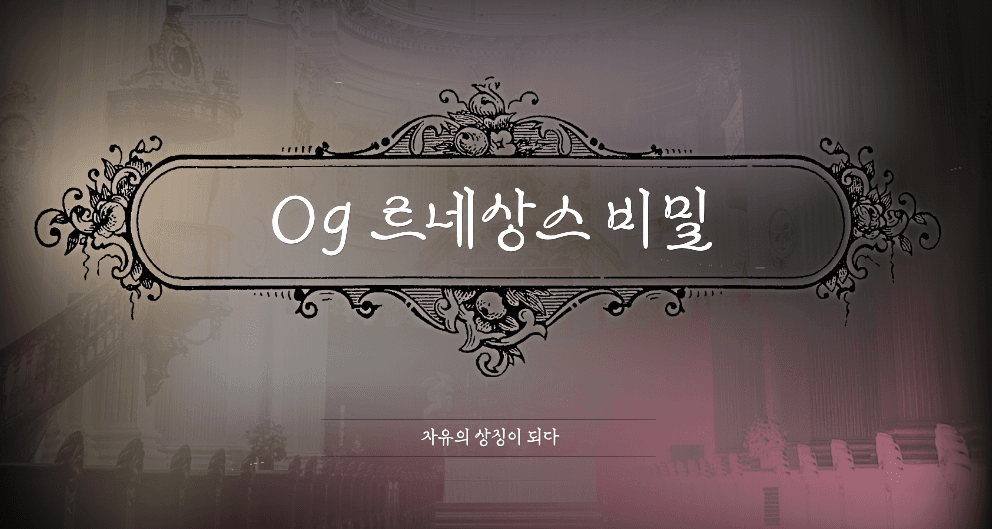
OG르네상스 비밀 — 온글잎에서 배포하는 무료 폰트입니다. 고전적인 분위기를 독특한 필체로 풀어낸 장식체
온글잎에서 나온 손글씨 서체입니다. 온글잎은 사용자가 종이에 글자 몇 개를 직접 쓰면 인공지능이 한글을 통째로 만들어 주는 서비스였고, 폰트 이름도 손글씨를 제공한 사람이 직접 붙였습니다. 이 서체도 2023년에 어느 이용자의 글씨로 만들어졌는데, 성씨 이니셜만 공개돼 있고 르네상스 비밀이라는 이름을 왜 붙였는지도 알려져 있지 않습니다.
페이지에 있는 디자이너의 한마디는 온글잎이 모든 폰트에 자동으로 넣는 문장이라 조형 설명이 아닙니다. 그래서 제작자가 남긴 형태 이야기는 따로 없습니다. 한글은 2,780자입니다.